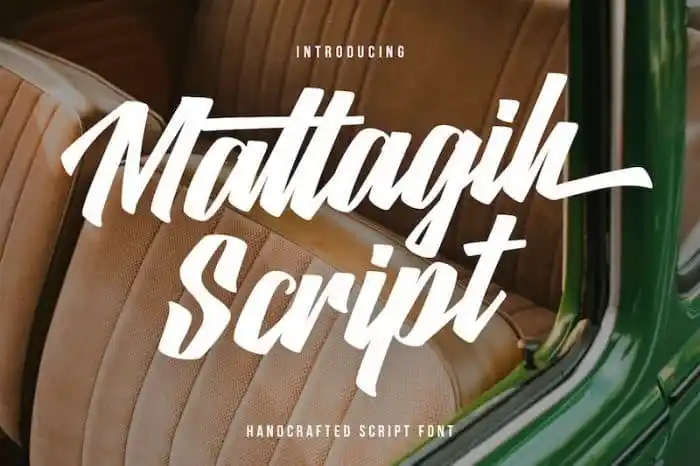
A Matlagih Brush Font é uma elegante fóntica script com traços fortes e agressivos que captura a atenção imediatamente. Seu design único permite-lhe adaptar-se de forma natural tanto para projetos de marca, logomarcas, tipografia de letras e outras empresas de tipos médios e de pequeno porte. Cada detalhe foi cuidadosamente pensado por Maulana Creative em 99designs, garantindo que você possa personalizar sua fóntica de acordo com suas necessidades específicas. Esta fonte é perfeita para quem busca uma fóntica que transmita estilo e atinja seu público-alvo de maneira eficaz, seja para um site corporativo ou a capa de um livro. Experimente a Matlagih Brush Font em sua próxima peça gráfica e impressione seus clientes com sua elegância contida.